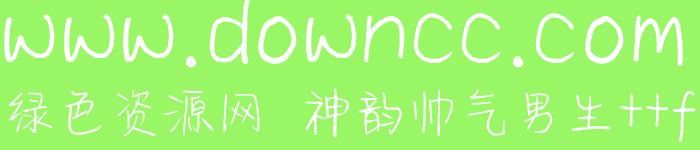
miui神韻帥氣男生體讓你感受到字體中的獨(dú)特男生氣質(zhì),讓你盡情的體驗(yàn)到使用這款字體的樂(lè)趣,給你精彩的視覺(jué)享受,而且在各種場(chǎng)合都能夠使用這款字體呢!
舒適的使用效果
精美的視覺(jué)體驗(yàn)
獨(dú)特的書(shū)寫(xiě)效果